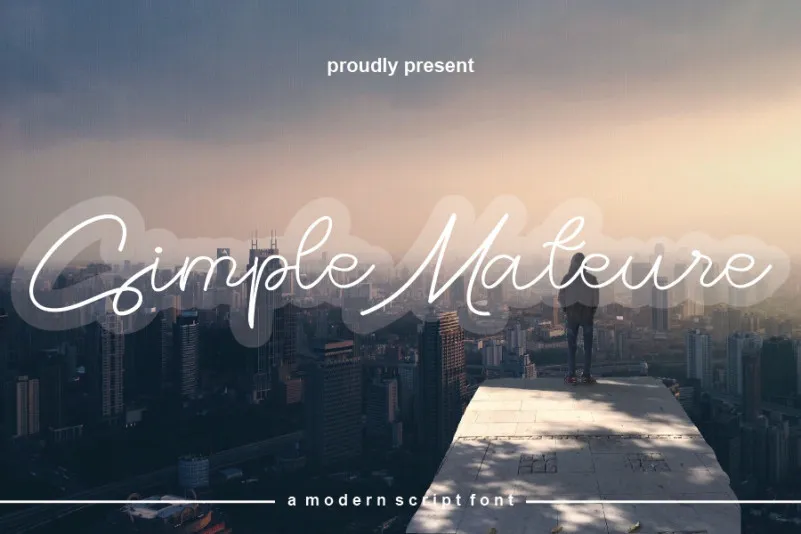
Simple Mateure Font – Download Grátis
A fonte “Simple Mateure Font” é uma ótima escolha para quem busca uma escrita elegante e versátil que se adequa a diversas necessidades de design. Este é um tipo feito especialmente para aqueles projetos onde uma mão realista e personalizada é essencial. Seu tom acolhedor, ao mesmo tempo desconcertantemente interessante, tornará suas ideias práticas em verdadeiras obras de arte. A fonte “Simple Mateure Font” oferece tanto flexibilidade quanto alegria para cada projeto que ela cobre, permitindo explorar infinitas variações e aplicações. Estamos certos de que você vai se divertir muito com este tipo bonito. Sempre que precisar de uma letra realista ou quer experimentar algo um pouco diferente, o “Simple Mateure Font” é a escolha perfeita para você.